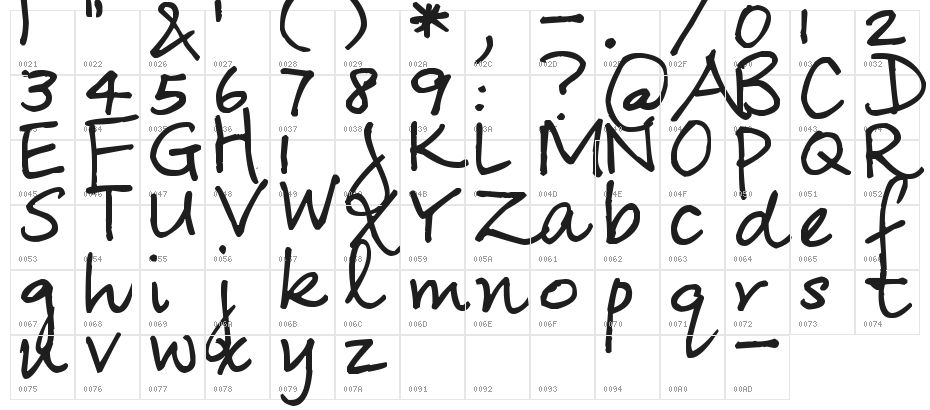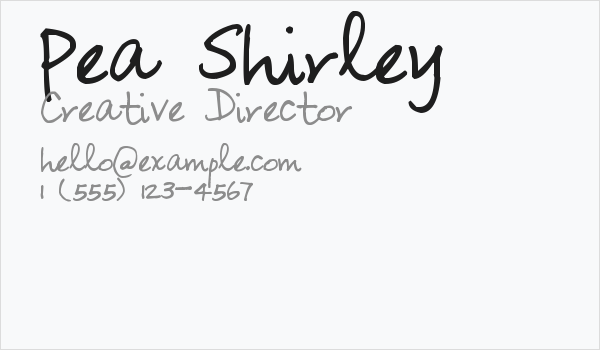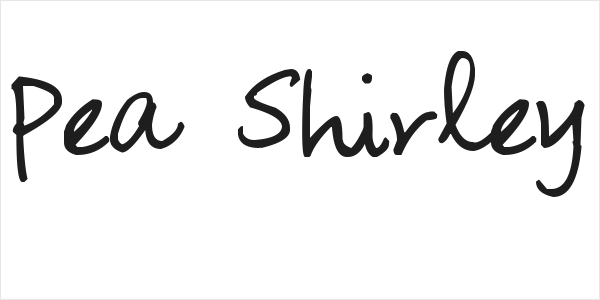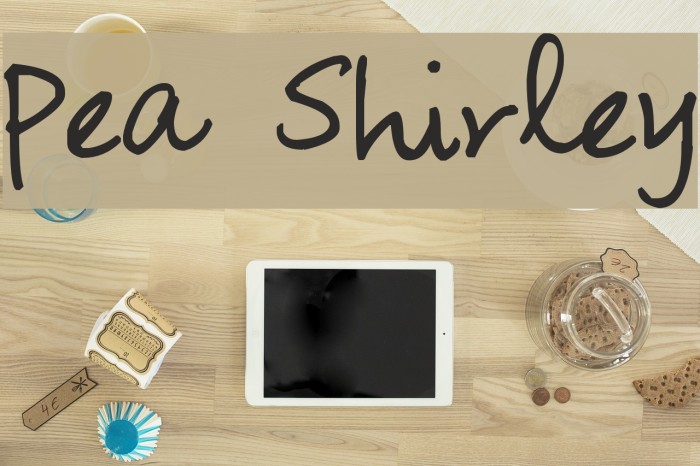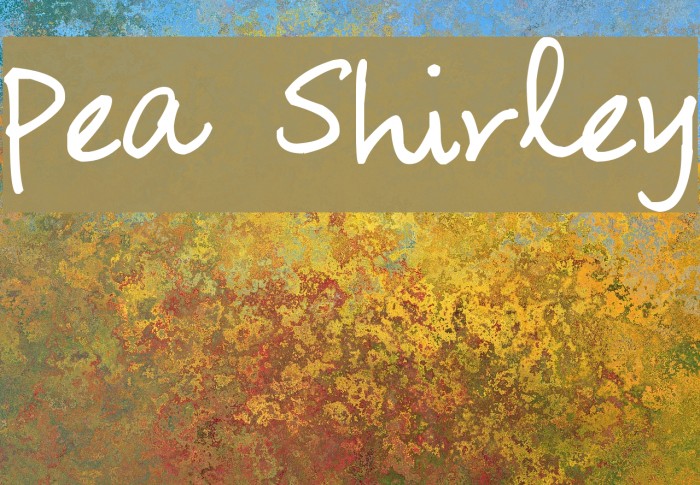
Pea Shirley Font
| Stile generale | Casual, Playful |
| Caso d'uso | Headlines, Informal text, Personal projects |
| Progetti proposti | Ideal for greeting cards, invitations, personal branding, and casual design projects. |